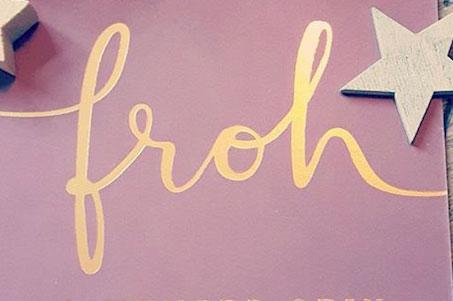
Schrift für Weihnachten
Hallo Leute, suche folgende oder ähnliche Schrift für eine feierliche Karte. Vorne und hinten mit langem Schweif auslaufend, siehe Beispiel.
Es stammt von einer Weihnachts-Karte. Habe diese mal fotografiert als Beispiel. Brauche die Schrift auch für eine Karte, nicht fürs Web.